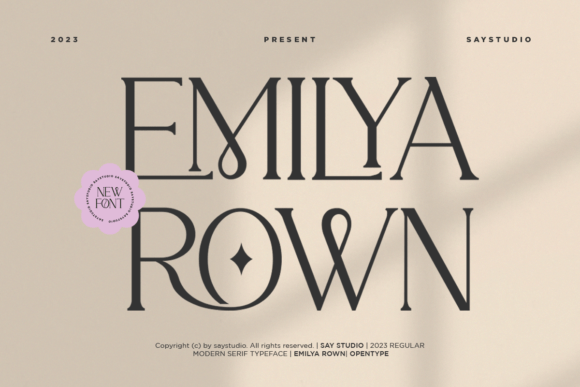
Emilya Rown
適切なデザイン要素を見つけるのは難しい場合がありますが、Emilya Rownは作品を即座に引き立てる優れたコレクションを提供します。
POD(オンデマンド印刷)製品、結婚式の招待状、またはソーシャルメディアのグラフィックを作成している場合でも、Emilya Rownは理想的です。